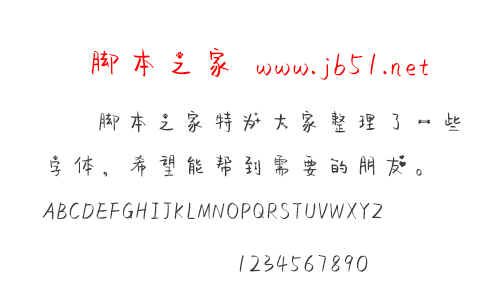
做你的狗子字體是文道字庫推出的一款個(gè)性藝術(shù)字體,字體自帶狗頭、bulingbuling星星、愛心、狗爪子等裝飾效果,風(fēng)格比一般的字體更有特色,具有很好的視覺感,適合應(yīng)用于藝術(shù)設(shè)計(jì)、平面宣傳設(shè)計(jì)、網(wǎng)頁設(shè)計(jì),書法字帖等領(lǐng)域,歡迎喜歡做你的狗子字體的朋友前來下載使用。